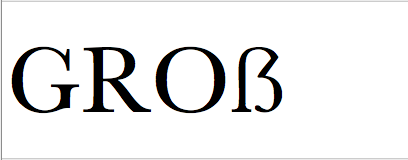
Schrift-Kombi für Projektarbeit im Bereich der Geschichtswissenschaften
OK, an deiner Uni wird da halt auch nicht groß Wert drauf gelegt – gestalte halt einfach nicht zu viel, damit kann man sich verzetteln und der Inhalt leidet – nimm nur eine Schriftart die das hat was du brauchst (regular, bold, kursiv (das brauchen Historiker immer :D ))
ein Pendant zur Arial wäre noch eine Akzidenz Grotesk
Wenns dann mal publiziert werden soll lass nen Grafiker ran – erspart dir auch viel Stress
Wenn die Vorgabe »neutral« lautet, würde ich nicht groß über Themenbezug nachdenken und eine Garamond nehmen – Stempel, Adobe Pro, was auch immer. Baskerville würde auch funktionieren (ich mag übrigens die von Storm sehr, gerade die Kursive :biglove:). Und wenn du scheinbar einen Faible für diese Schrift hast, hast du auch für die Zukunft ein gutes Arbeitstier …
Überschriften vielleicht Futura oder Avenir als Kontrast oder einfach mal mit Versalsatz, Schriftgröße oder Kapitälchen der gleichen Schrift rumprobieren und gut ist. Der Satz selber ist fast wichtiger als die Details in einer Schrift, die in Lesegröße keiner bemerkt ;-)
Gestaltungsansätze
Mag ja sein, aber Historiker gestalten nicht, sie beschreiben. Und das möglichst in gewohnter Weise. Deine hier vorgetragenen Vorschläge mögen an einer Kunstakademie angemessen sein, aber nicht im geschichtswissenschaftlichen Umfeld.
Leider gibt's die Garamonds ja auch in allen möglichen Variationen:
Adobe Pro, Premier Pro, Cormorant, Stempel... mir fällt da die Entscheidung schwer!
Die Baskerville ist der Hammer :-P
Stempel
Die ist leider etwas dürr und in Bezug auf die Seitenabstände der Zeichen miserabel. Aber grundsätzlich ist sie unter den digitaliserten Garamonds meine Favoritin.
Wie wäre es mit einer unechten Garamond wie der ATF Garamond als Alternative? Oder der Verdigris?
Oder eine andere klassische Schrift: Die Caslon, u. z. die WilliamsCaslon (Font Bureau). Die ist allerdings auch deutlich teurer als 100 Euro. Aber ebenfalls ausgesprochen gut lesbar.
Die Baskerville ist der Hammer
Nimm dann die, Du musst schließlich mit dem Aussehen der Arbeit zufrieden sein, denn Du repräsentierst Dich und Deine Gedanken damit.
Auf dem Mac gibt's eine Baskerville vorinstalliert... wieviel besser ist die kostenpflichtige im Vergleich?
Ja, diese Verdigris. Aber ich bin gerade ziemlich vom Preis überrascht. Falls die in Frage kommt, käme auch die Sabon Next in Frage.
wieviel besser ist die kostenpflichtige im Vergleich?
Aber man sagt, dass die von Storm die beste Baskerville sei, so wie die Stempel Garamond die schönste Garamond sei. Das liegt im wohl im Auge des Betrachters.
Die Stempel Garamond hat einen genialen Zeichen-Rhythmus. Eines meiner Lieblingsbücher ist in ihr gesetzt. Falls die Stempel Garamond, die derzeit als Font erhältlich ist, die Basis für den Druck war, hat der Drucker ordentlich Farbe dazugeben. In Bezug auf die Lesbarkeit ist sie in diesem Buch kaum zu schlagen.
Dann werde ich mir die beiden Baskervilles, die Stempel Garamond und die Sabon Next, sowie die Caslon morgen in Ruhe abgucken!
Leider kann man die verschiedenen Fonts auf MyFonts.com sehr schlecht vergleichen...
Das stimmt. Du solltest ohnehin wegen unterschiedlicher Versionen bei den Foundries vorbeischauen, also ihren Websites. Linotype bietet, soweit ich mich erinnere, eine Pro-Version an, die in Bezug auf den Zeichenvorrat besser ausgebaut ist als die Adobe-Version. Version bedeutet in diesem Kontext aber nicht, dass sich die Zeichenformen oder die Zurichtung bzw. das Kerning unterscheidet. Die Lieblosigkeit, mit der sie zugerichtet wurde, ist angesichts ihrer grundsätzlichen Qualität eine Schande. Zurichtung und Kerning sind bei der Stempel Garamond wirklich nicht gut. Die Sabon Next ist in Bezug auf Zurichtung und Kerning ziemlich perfekt. Und in Bezug auf die anderen Eigenschaften, die die Qualität einer Schrift ausmachen, auch.
Jo … da ist dann auch die Avenir oder Futura zum Kombinieren dabei. Ist zwar nicht sonderlich originell und hat nicht viel mit Erfrischungskur für Mengensatz zu tun, aber die Aufgabenstellung »anders als Calibri/Cambria ohne große Investition« wäre erfüllt.
Das liegt auch an den Versalien, die ja außerordentlich groß im Verhältnis zu den Gemeinen sind. Das ist bei Storm nicht so und ergibt ein gleichmäßigeres Schriftbild (was hier ja wünschenswert ist) – das spräche für die Investition :nicken: